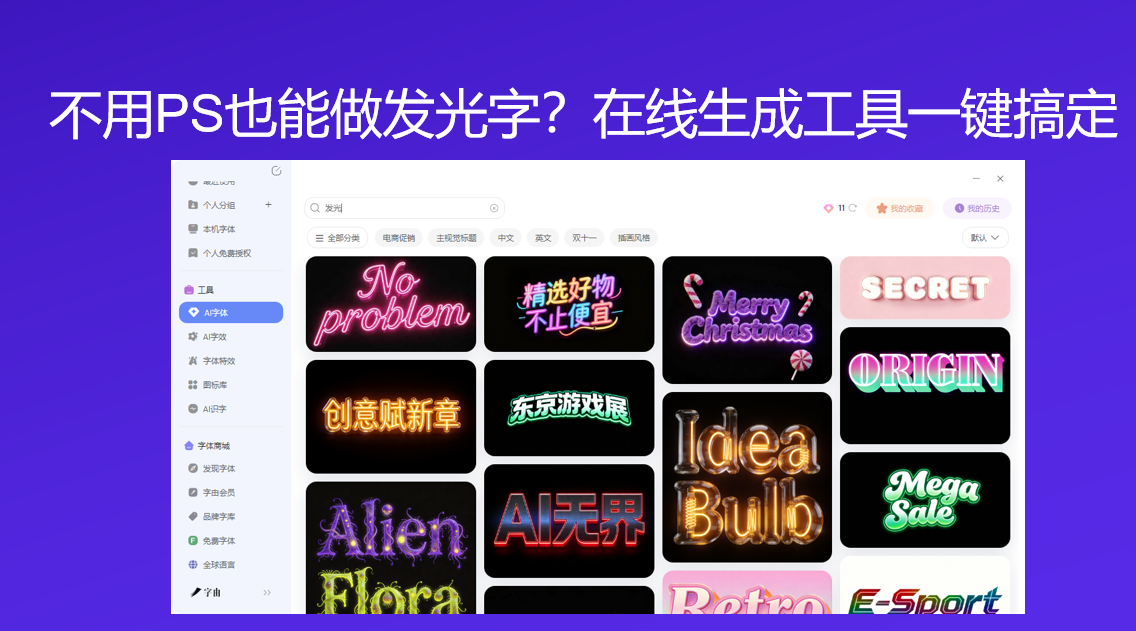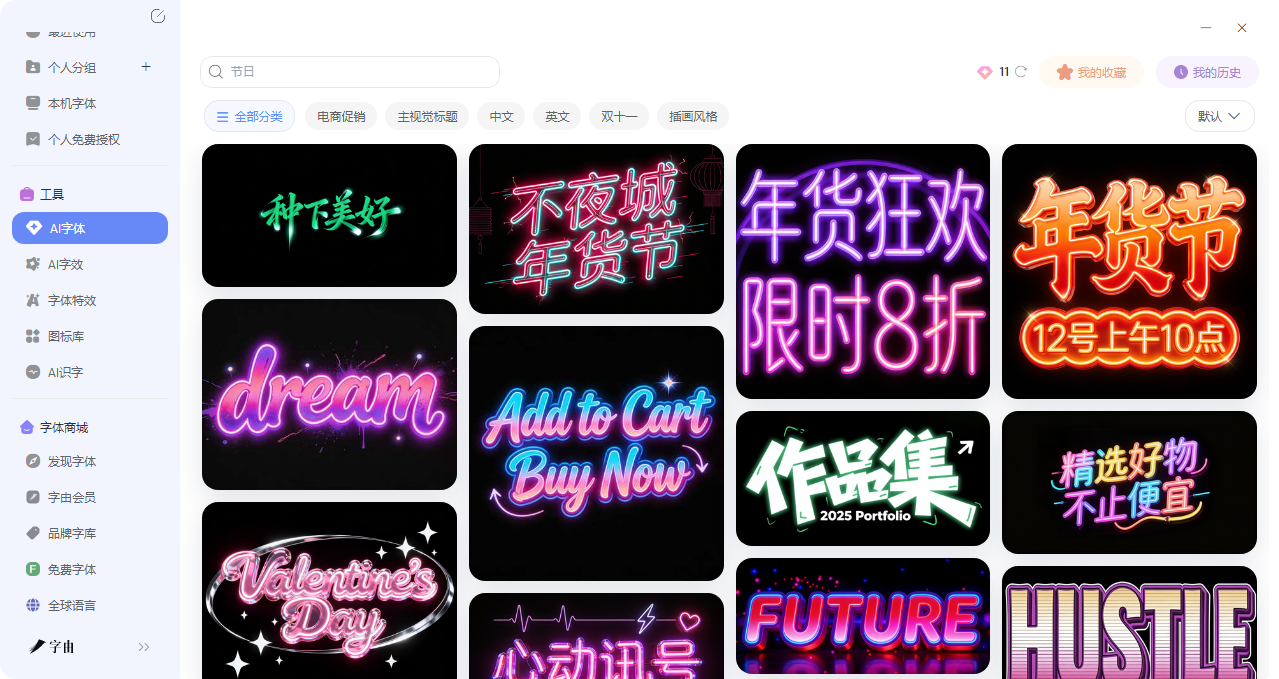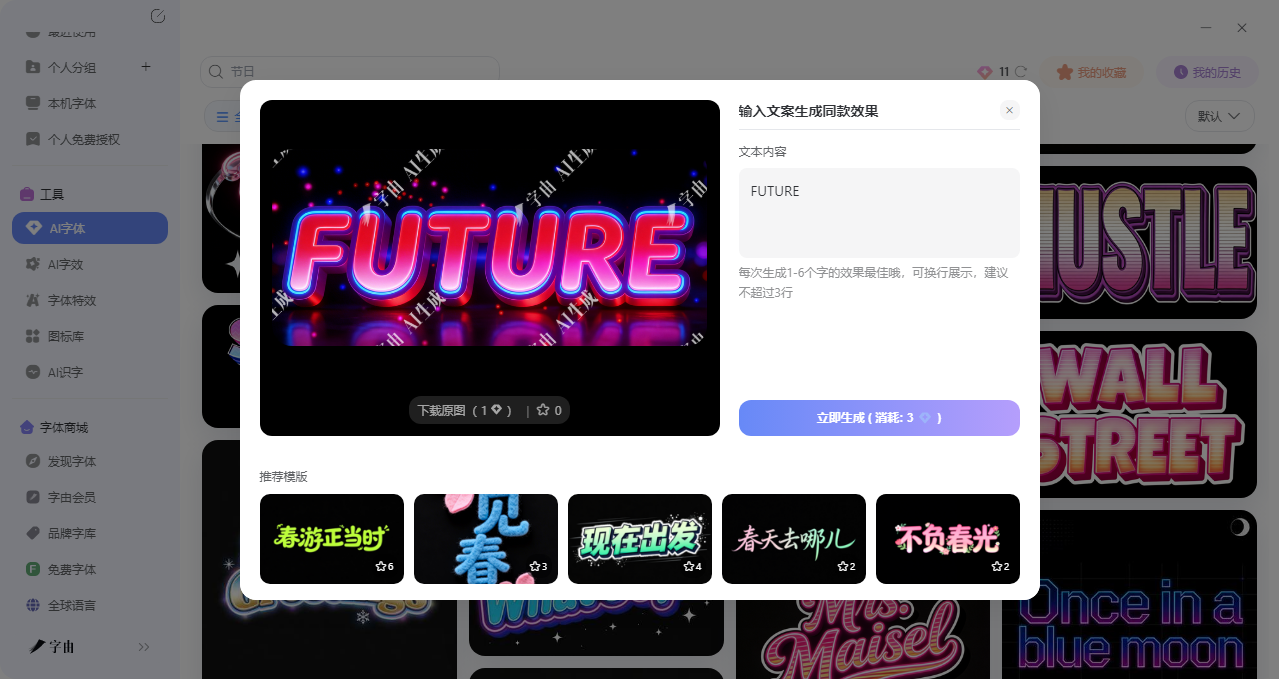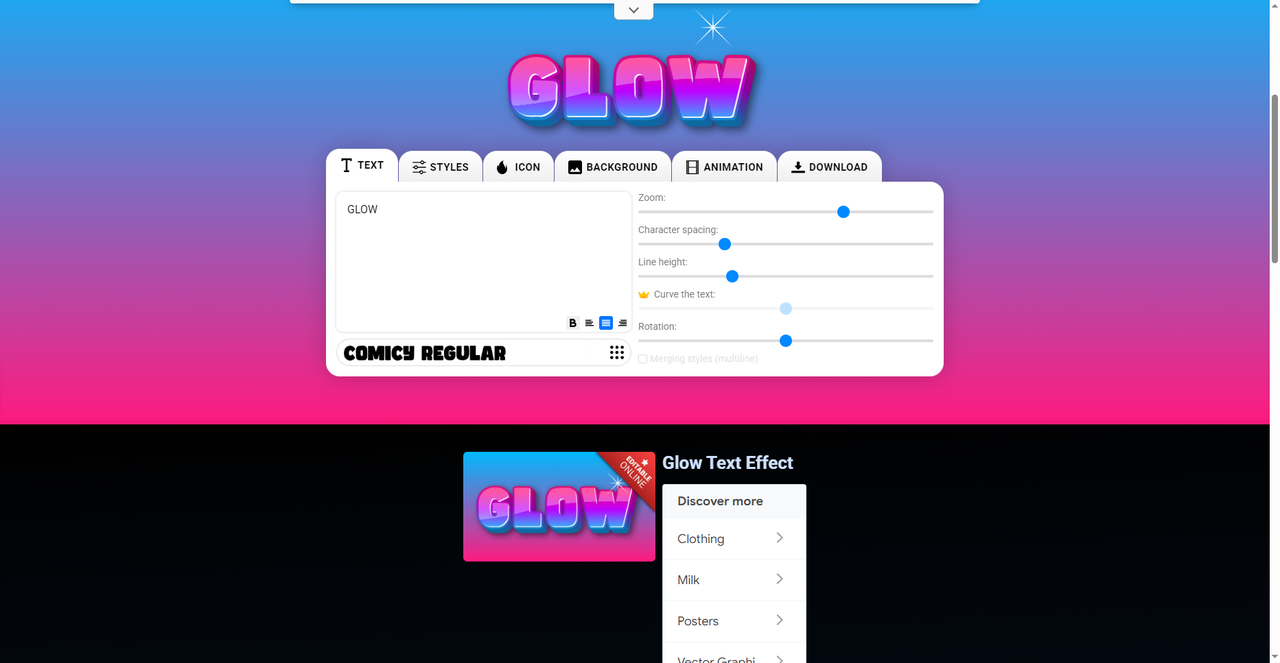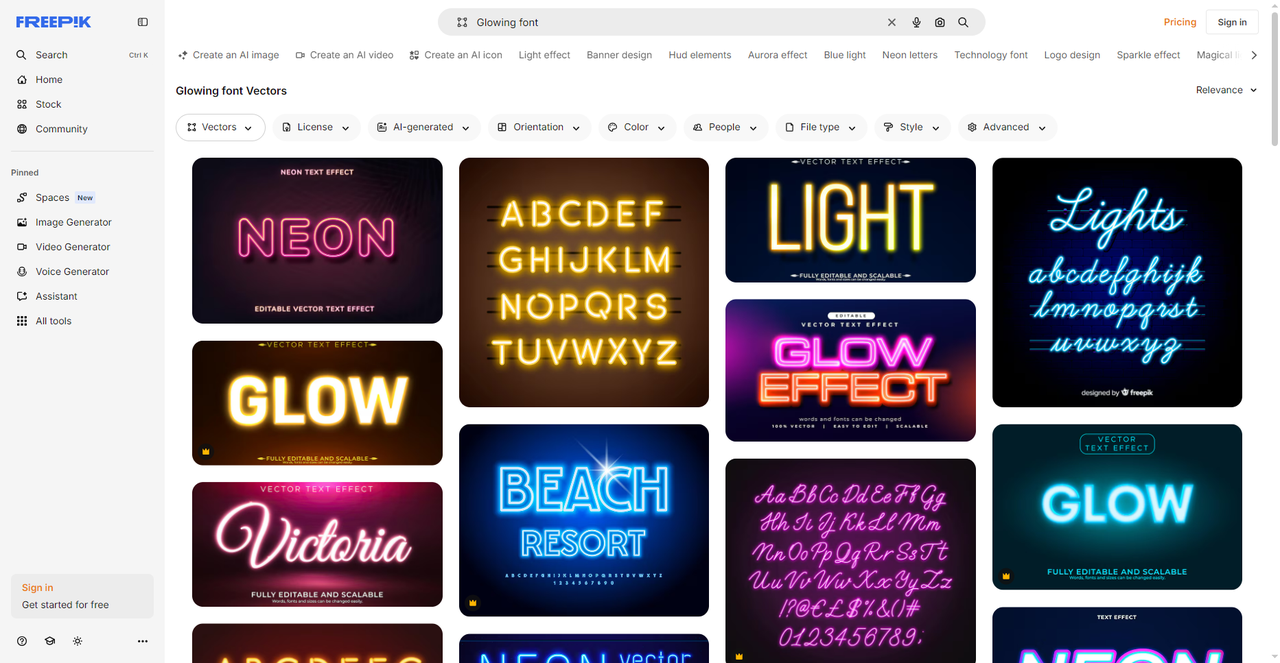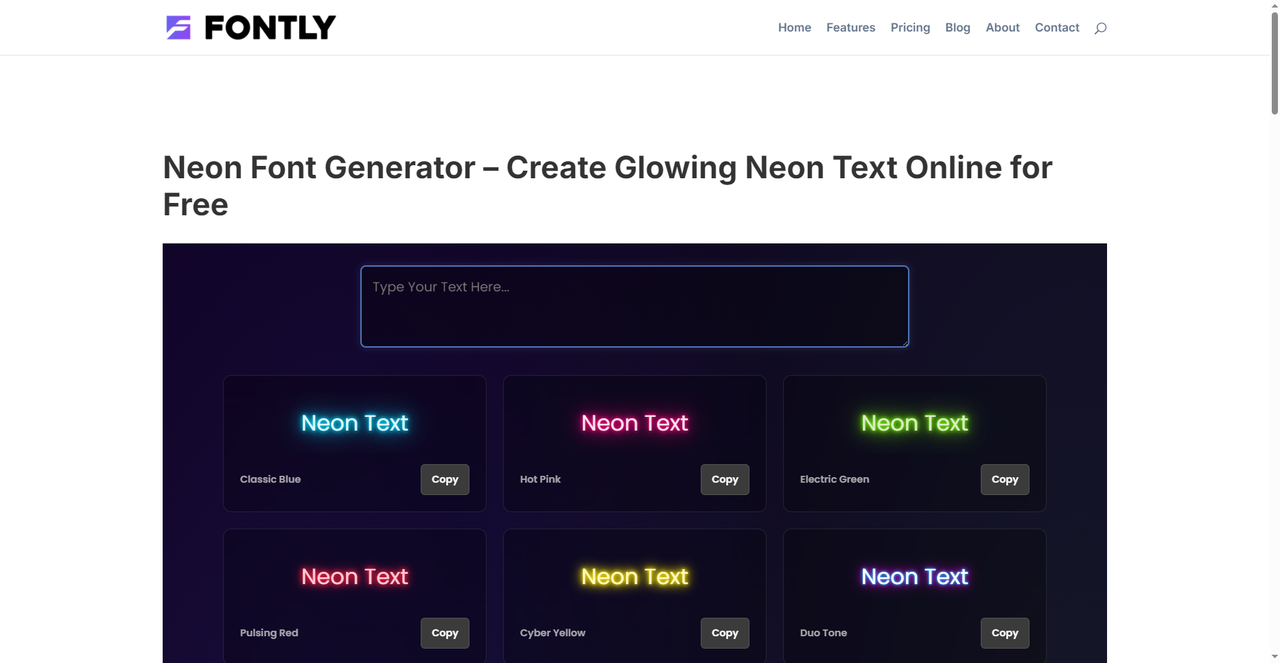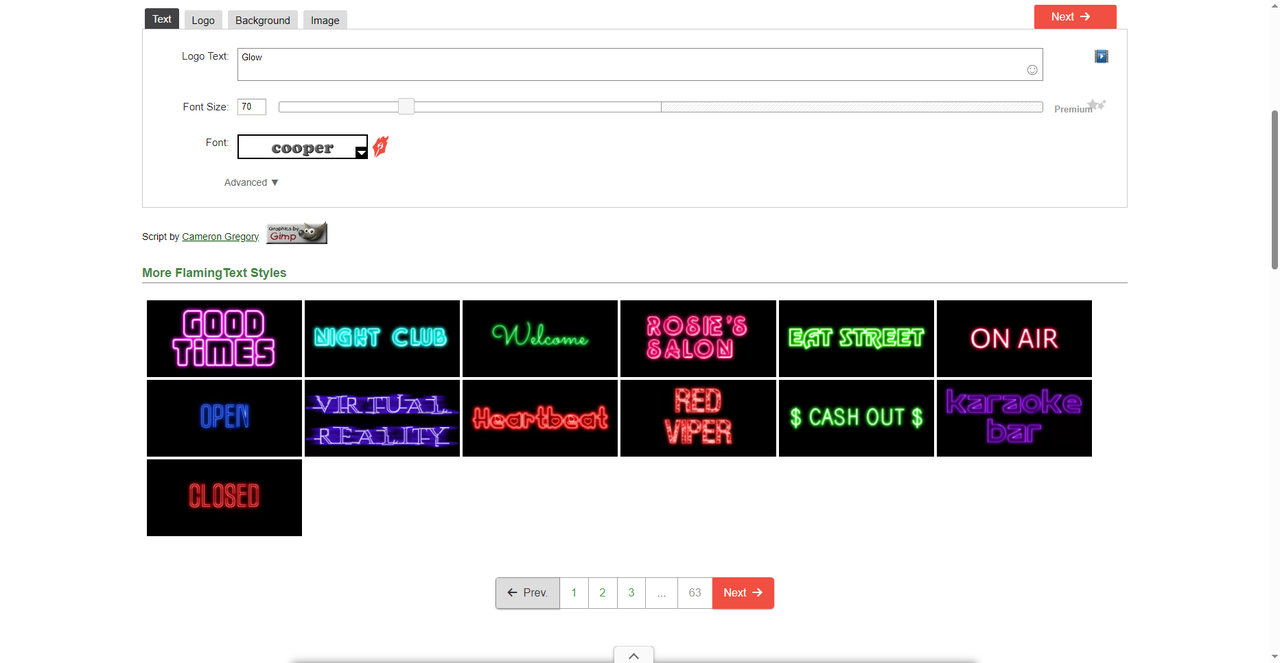
以前要做发光字的时候第一想到的工具肯定是PS,新建图层,打字,然后开始调图层样式——外发光、内发光、投影、渐变叠加…这样一通操作下来没有个半个小时到一个小时是办不下来的,而且如果对字体效果还有更高要求的话,花费的时间无疑会更长,甚至还得去After Effects里折腾。但是直到我发现了有专门的发光字体在线生成工具,只需要输入你想要的文字,选择对应的文字特效风格,点一下,不超过一分钟就可以生成了,根本不用打开PS。那么今天我就为大家筛选了5 个亲测好用的发光字体在线生成工具,需要的记得码住!
第一个要推荐的发光字体在线生成工具是字由。字由不仅作为字体库,它还有着丰富的AI 工具,其中就包括AI 字体,专门用来生成各种风格的艺术字,发光效果当然也在其中。
下面是生成发光字的具体步骤:
- 第二步:进入AI字体页面后,在搜索框里输入“发光”“霓虹”“光效”“光晕”等关键词,系统会自动筛选出所有带发光效果的模板。你也可以直接点进“科技感”“霓虹风”等分类里慢慢翻。
- 第三步:搜索结果会展示各种发光风格的预览图,比如
- 霓虹灯管效果(带玻璃管质感,像夜晚的招牌)
- 柔和光晕发光字(边缘有朦胧光晕)
- 彩色渐变发光(多种颜色过渡)
- 科技感冷光(蓝紫色调,适合数码产品)
- 荧光涂鸦效果(像街头涂鸦)
每个模板都有预览图,选一个和你设计风格搭的来生成即可。
- 第四步:点击选中的模板,进入编辑页面。在输入框里填你想要生成发光效果的文字(比如“开业大吉”“限时特惠”“霓虹之夜”)。
只需要简单的几步就可以生成了,完全不需要费力从头开始设计!
2、GLOW TEXT
这是一款可以调节细节的发光字生成神器,它不仅有预设的发光效果,还提供了丰富的调节选项,让你能精细控制最终效果。核心功能主要有以下几项:
- 样式选择:左侧有多种发光风格预设,点击即可应用。
- 图标与背景:可以添加图标作为装饰,或者更换背景颜色/图片。
- 动画:支持生成动态发光字(GIF或视频格式),适合做短视频标题。
参数调节:
- 字符间距
- 行高
- 文字曲线
- 旋转角度
- 发光强度(通过Zoom滑块)
- 字体选择:内置多种字体,如“COMICS REGULAR”等。
这个工具特别适合需要精细调整发光效果的场景。比如你想要文字稍微弯曲一点,或者想调整每个字之间的间距,在这里都能轻松实现。
3、FREEPIK
Freepik 是全球知名的设计资源平台,里面有着海量发光字体模板,可以直接在网页编辑使用。不过也有很多人用它找矢量图、PSD模板就是了。其实在Freepik上搜索“glowing font”或“neon font”,也能找到大量发光字体在线生成相关的素材。需要注意的是,每个模板都标注了“VECTOR TEXT EFFECT”,下载后可以在AI或PS里直接编辑文字内容,保留发光效果,风格涉及的也很多样,部分素材可以免费下载使用(标注“free”),商用需查看具体授权。
4、FONTLY
这是一个专门生成霓虹字体的生成器,多种发光风格都可以一键使用,你只需要输入文字,它就会自动生成16种不同风格的霓虹发光效果。而且每个风格后面都有“Copy”按钮,点击即可复制对应的CSS代码或图片链接。这个工具适合想要快速尝试多种发光风格的用户,不用自己调参数,直接“抄作业”即可。
5、Glow Text Generator(FlamingText)
这个网站就比较老了,但是功能什么的都很经典,应用也十分简单,输入文字,选择字体和大小,点击生成,就能得到发光字。具体使用步骤如下:
- 在主页输入文字(如“Glow”)。
- 可选的Tab有:Text、Logo、Background、Image,支持上传Logo进行组合。
- 调整字体大小(如70px)、选择字体(如Cooper)。
- 点击“Advanced”可以进一步微调。
- 下方会实时显示生成的发光字预览。
这个网站的最大优点就在于老牌可靠、有着多种样式,下载也十分方便,适合快速出图。
今天的内容就介绍到这里了!以前总觉得发光字体需要靠PS 一步一步设计出来,但是如今大不一样,可以依靠这些发光字体在线生成工具就能轻松地拥有发光字体,一切简单到不可思议。无论你是需要快速出图,还是追求精细控制,总有一款适合你。如果你想跳过所有麻烦的步骤,可以选择字由,只需要打开AI 字体,搜个“发光”,选个模板,几十秒后你想要的东西就可以立刻生成,谁不想拥有呢?